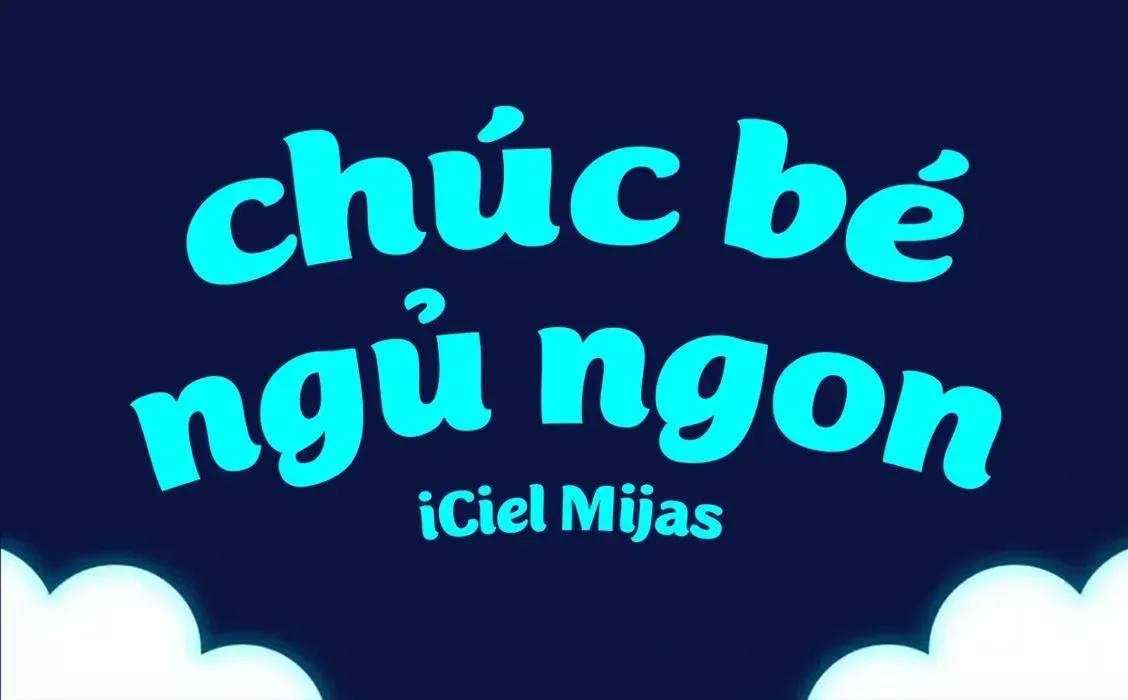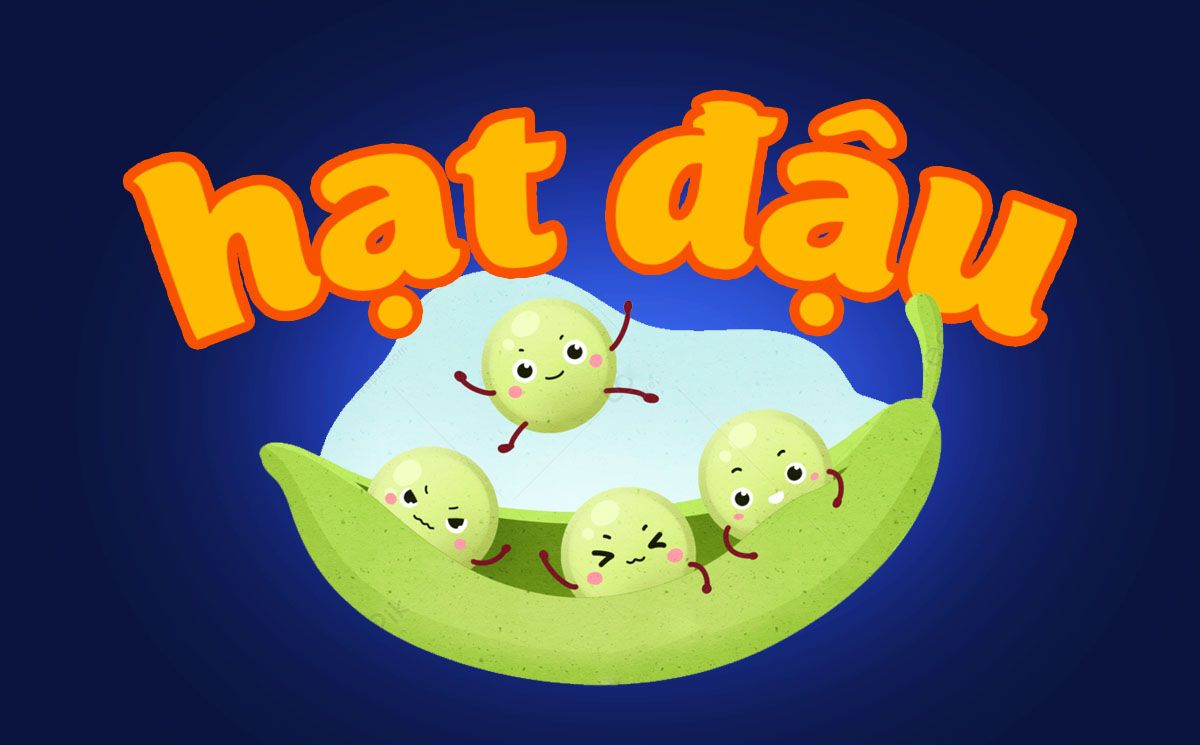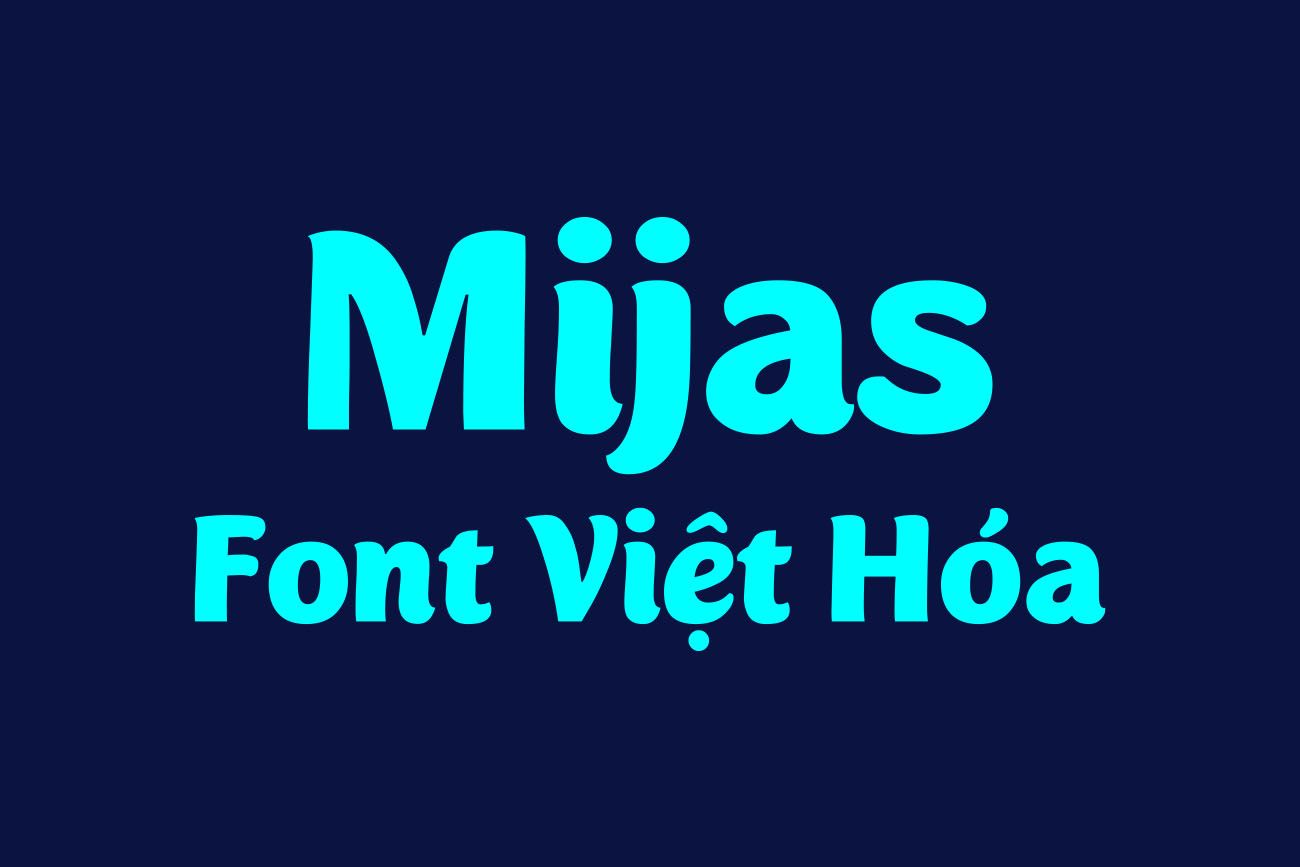
Nguồn gốc của font Mijas bắt đầu từ thiết kế của Paulo Goode, một nhà thiết kế nổi tiếng với những bộ chữ mang tính cá nhân cao, pha trộn giữa hiện đại và sáng tạo. Phiên bản iCiel Mijas Việt hóa do nhóm iCiel thực hiện đã bổ sung toàn bộ dấu tiếng Việt, giúp font có tính ứng dụng rộng rãi trong nhiều dự án tại Việt Nam.
Điểm đặc trưng của font iCiel Mijas nằm ở đường nét tròn trịa, dày dặn nhưng vẫn giữ sự mềm mại và cân đối. Các ký tự mang phong cách sans-serif nhưng lại toát lên sự ngộ nghĩnh, vui vẻ. Khi sử dụng, font này dễ dàng truyền tải cảm xúc tích cực, làm nổi bật nội dung thiết kế mà không cần quá nhiều hiệu ứng bổ sung.
Với phong cách hiện đại nhưng vẫn có nét thủ công tinh tế, iCiel Mijas đặc biệt phù hợp trong các thiết kế liên quan đến trẻ em, ẩm thực, thương hiệu sáng tạo hay các chiến dịch quảng cáo muốn tạo cảm giác thân thiện. Bạn có thể dùng font này cho poster, bìa sách thiếu nhi, bao bì sản phẩm, banner, logo hoặc thiết kế social media.
Sở hữu iCiel Mijas Việt hóa, bạn không chỉ có một font chữ đẹp mắt mà còn mang đến cho thiết kế của mình sự sinh động và khác biệt. Đây chính là lựa chọn lý tưởng để tạo ra những ấn phẩm thu hút và ghi dấu ấn mạnh mẽ với người xem.